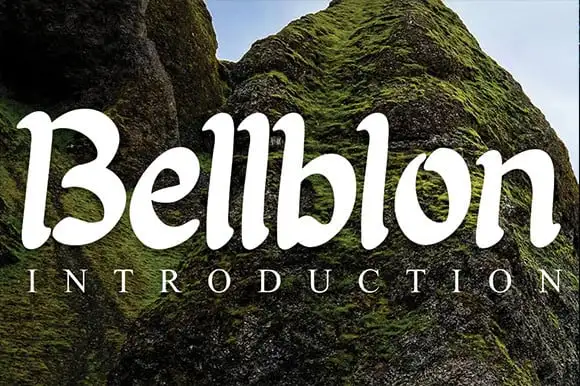
Bellblon Script Font – Fonte Grátis
Bellblon Script Font
A Bellblon Script Font é a nova tendência no mundo das fuentes, projetada para enriquecer sua identidade visual com elegância e sofisticação. Suas linhas fluidas e traços delicados tornam essa fonte perfeita para destacar seus trabalhos em ambientes que valorizam o toque pessoal e a expressão criativa. Escolha esta Bellblon Script Font para criar um estilo único em projetos variados, desde embalagens de produtos até design gráfico em edição. Seja para criação de logotipos e marca, ou para incorporar uma dose de personalidade em designs de mídia social ou redes sociais, a Bellblon Script Font pode ser sua chave para tornar seu projeto ainda mais irresistível. Adicione à sua paleta de ferramentas de design esta fonte script perfeita. Ela não apenas traz um toque de charme aos seus trabalhos, mas também oferece flexibilidade e sofisticação necessárias em qualquer tipo de projeto visual que você possa imaginar. Seja para projetos profissionais ou pessoais, a Bellblon Script Font é uma escolha inteligente que certamente vai impressionar ao destacar sua identidade única.